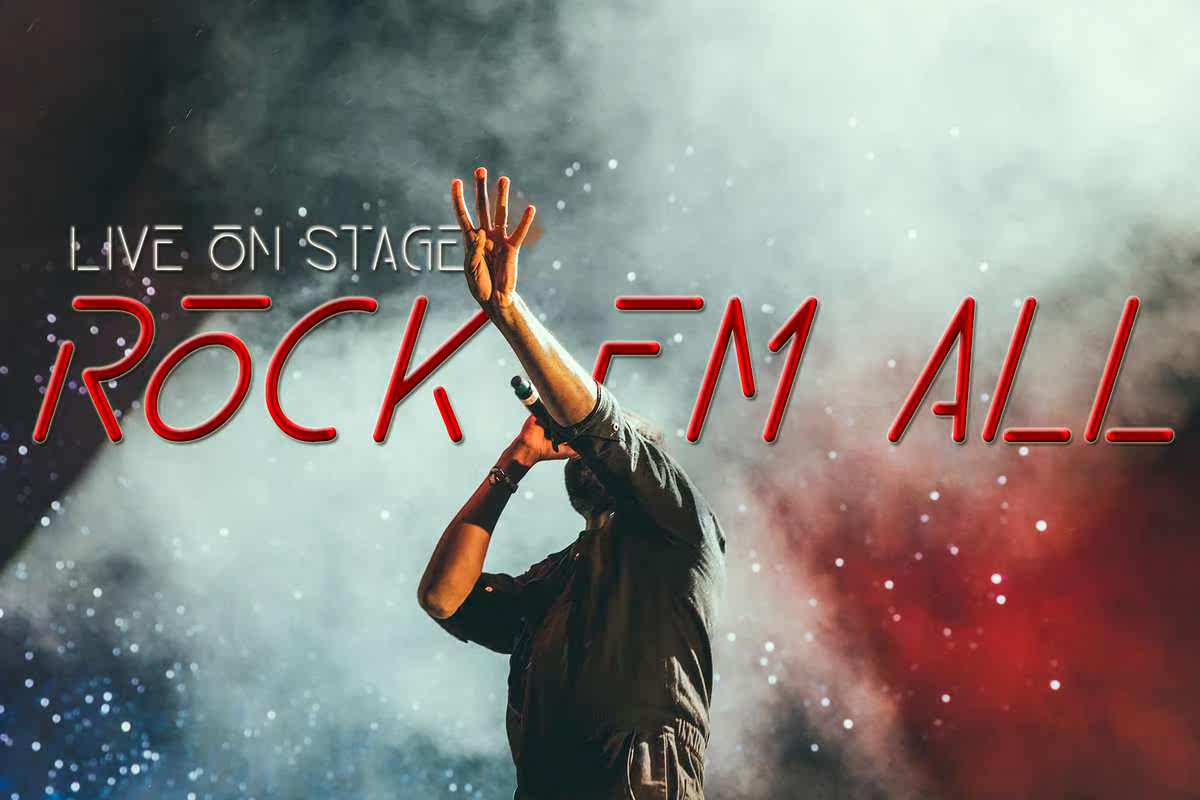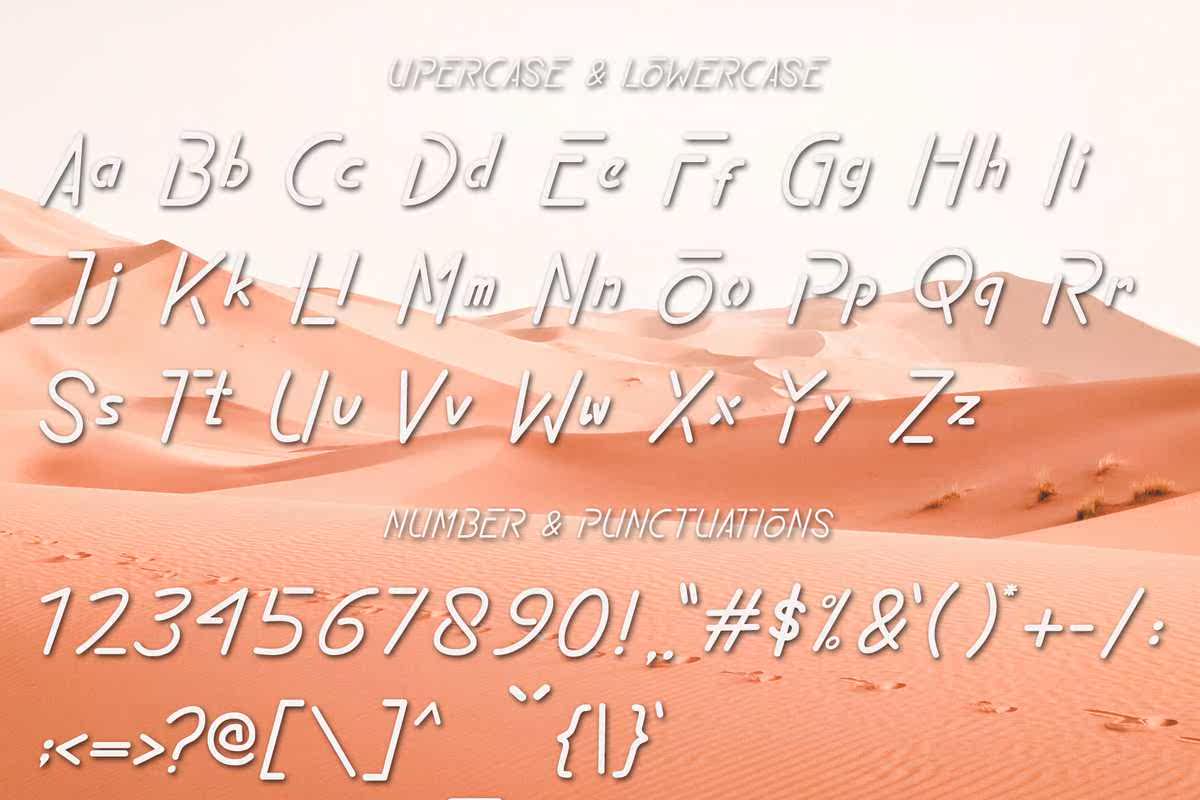
Portlandisamodernsans由HizartDesign提供。它是一款未来派的Sansserletter,将为您的设计带来独特的个性。Portlandisamodernsans在徽标、电影、包装设计、耐磨性、工艺设计、任何项目、书名、专辑封面、包装等方面都是完美的,还有更多。PortlandisModernsans由HizartDesign提供。它具有未来主义的sansserletter,将为您的设计带来流畅、优雅的个性。PORTLANDis在徽标、电影、包装设计、耐磨性、工艺设计、任何项目、书名、专辑封面、包装等方面都是完美的。